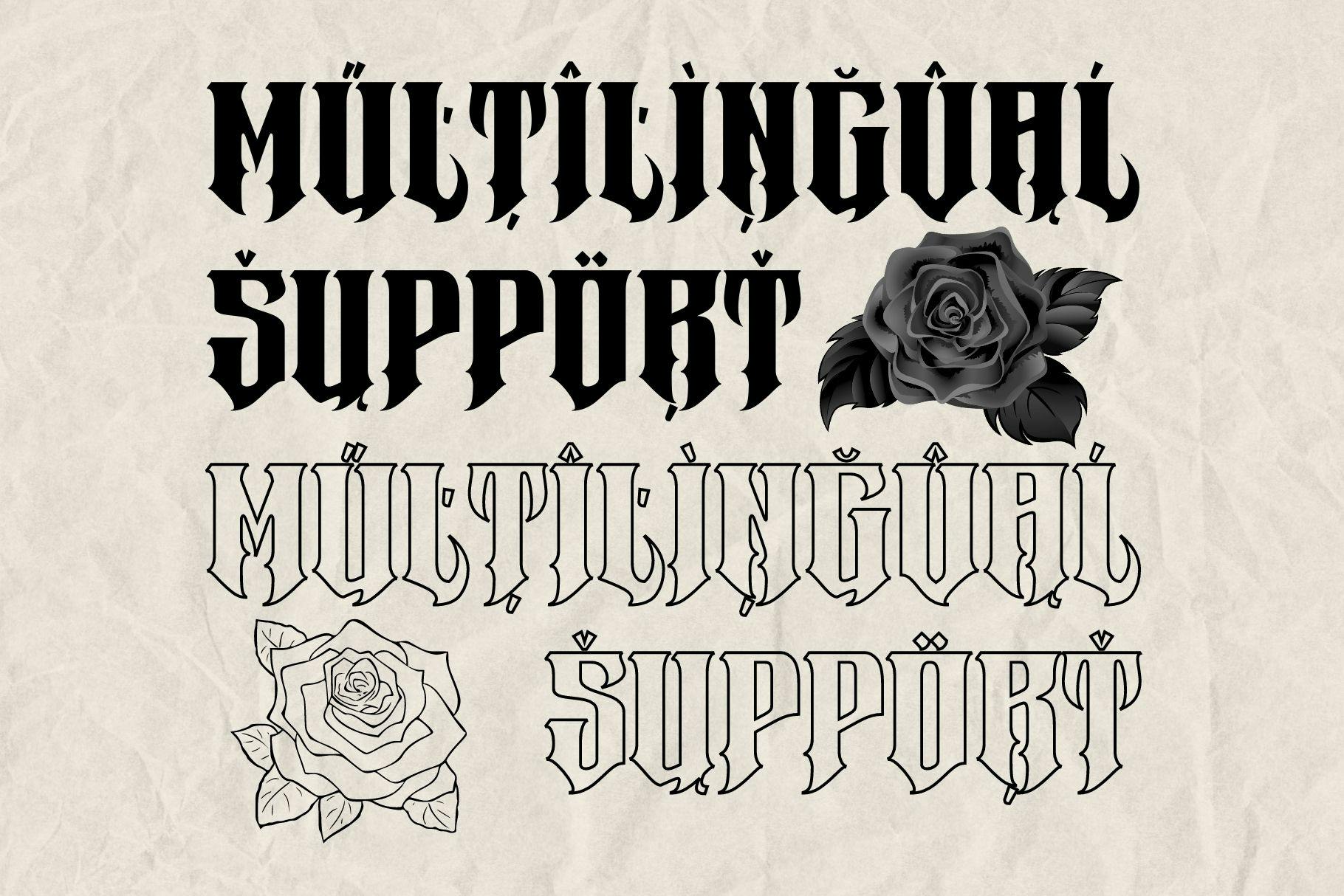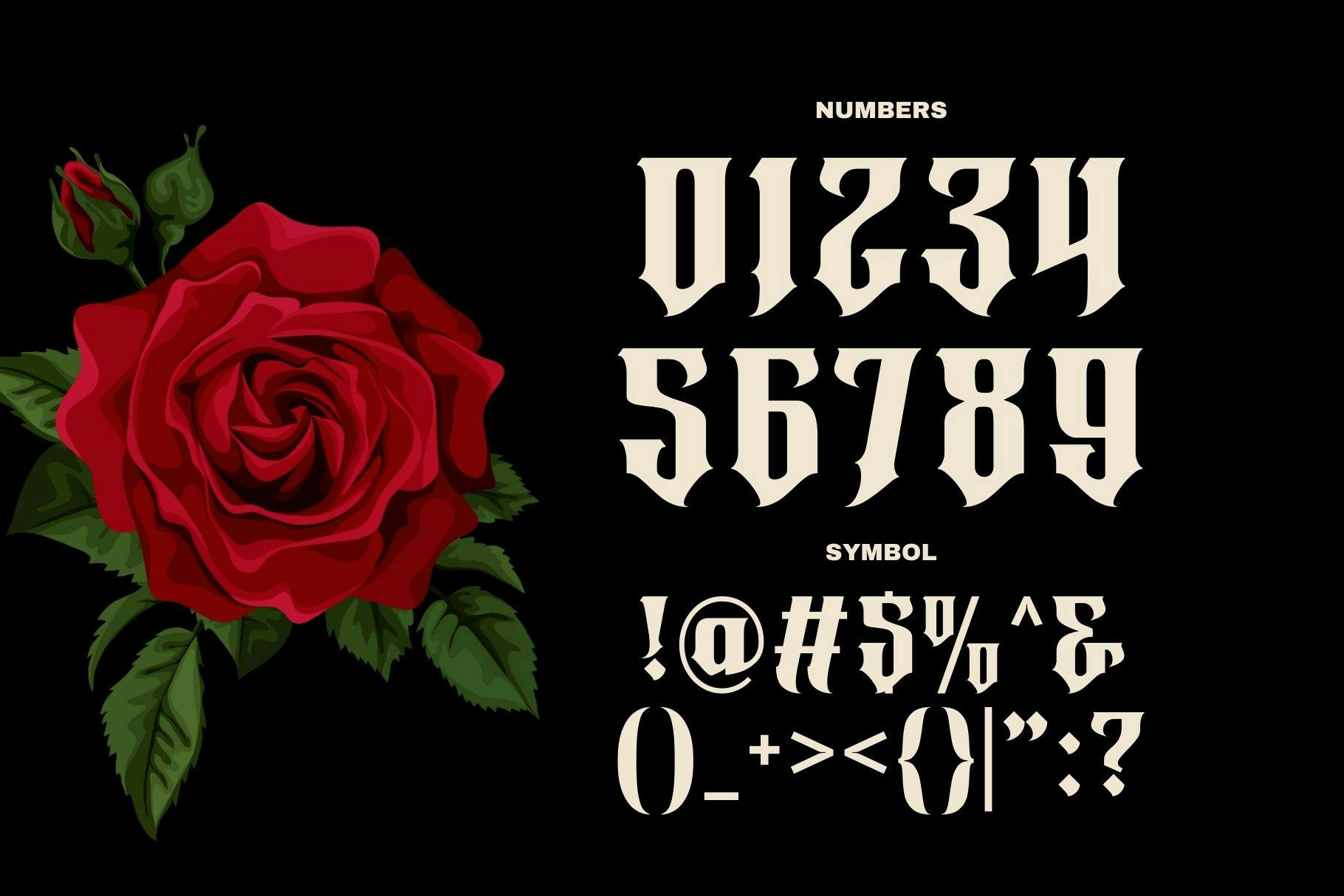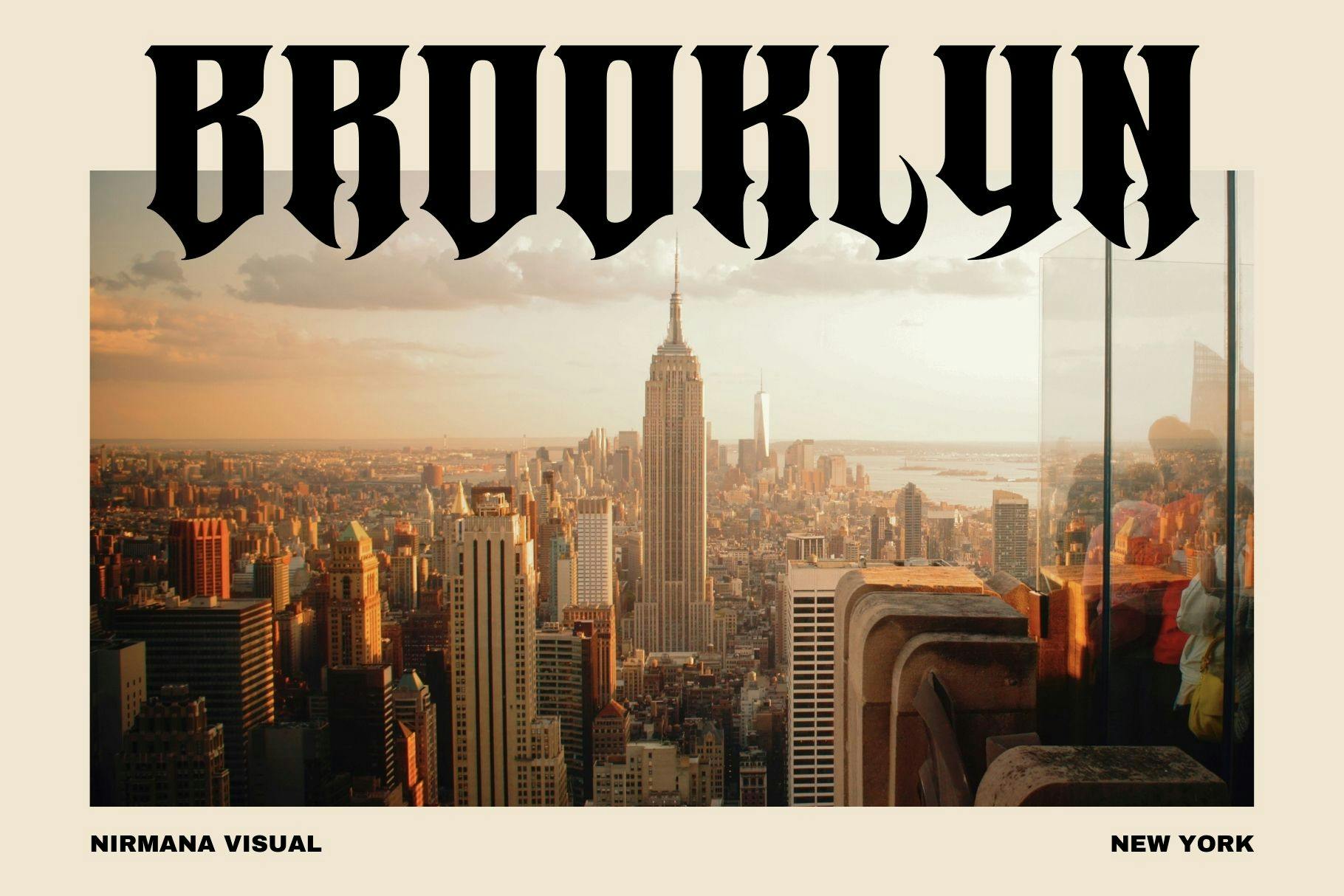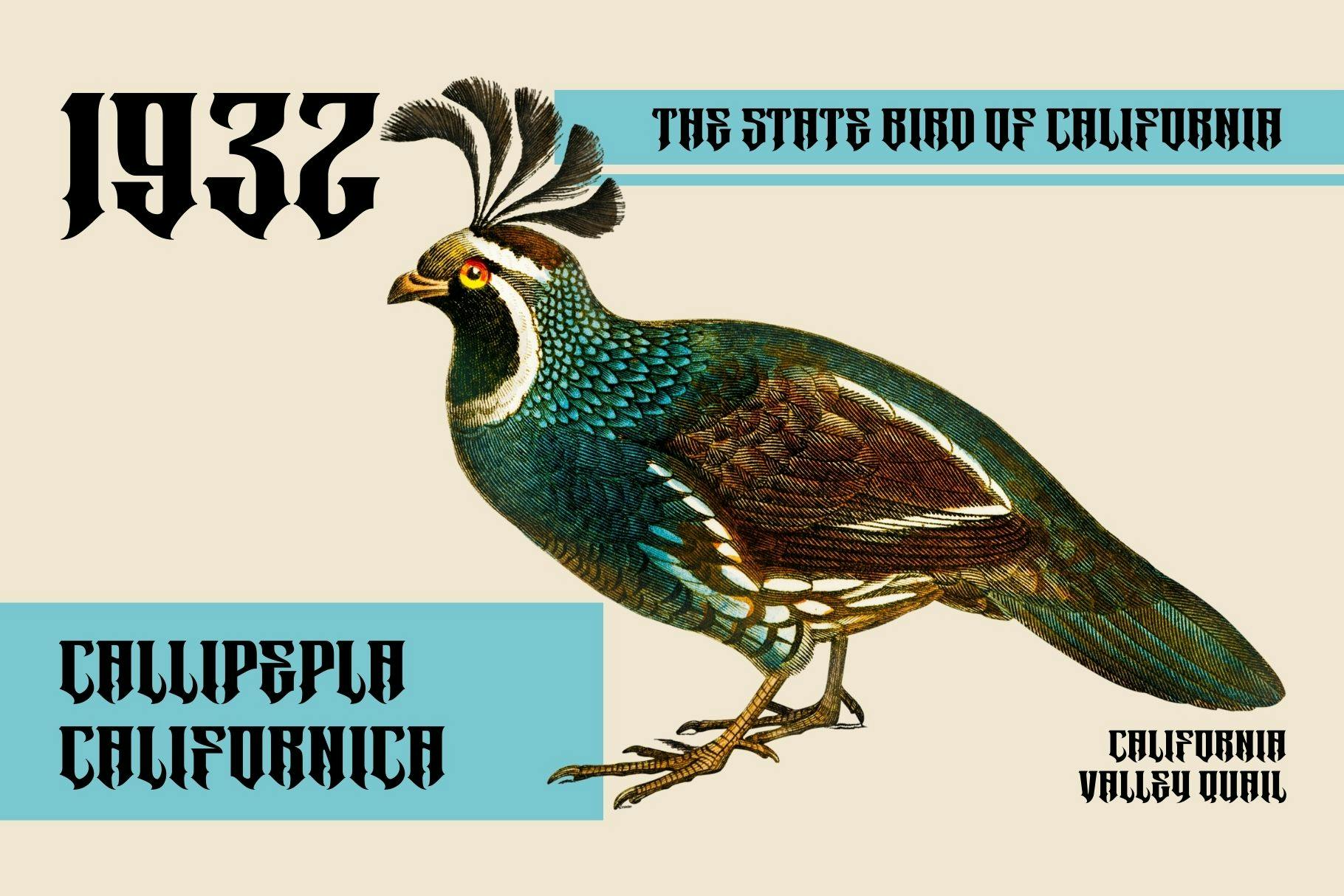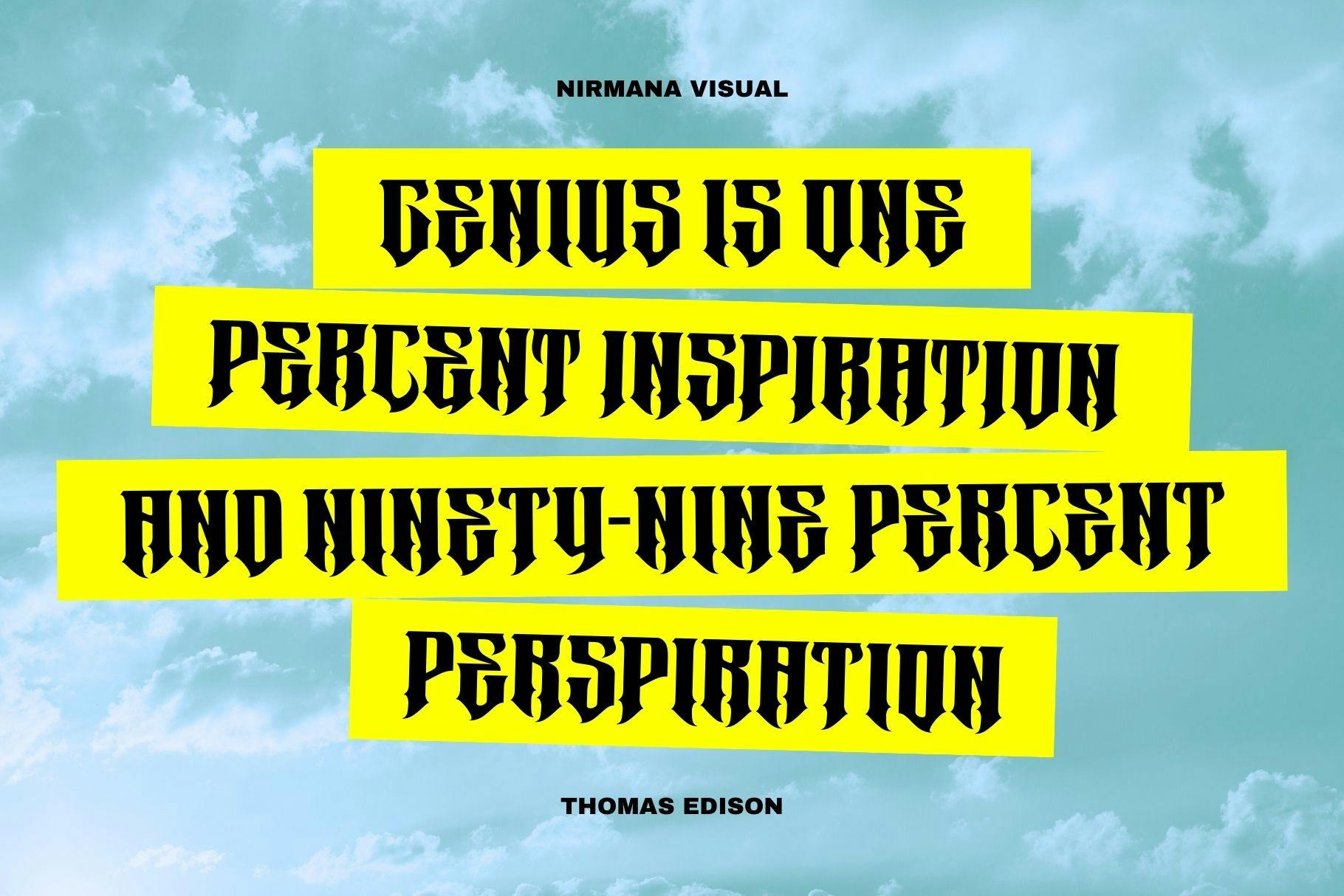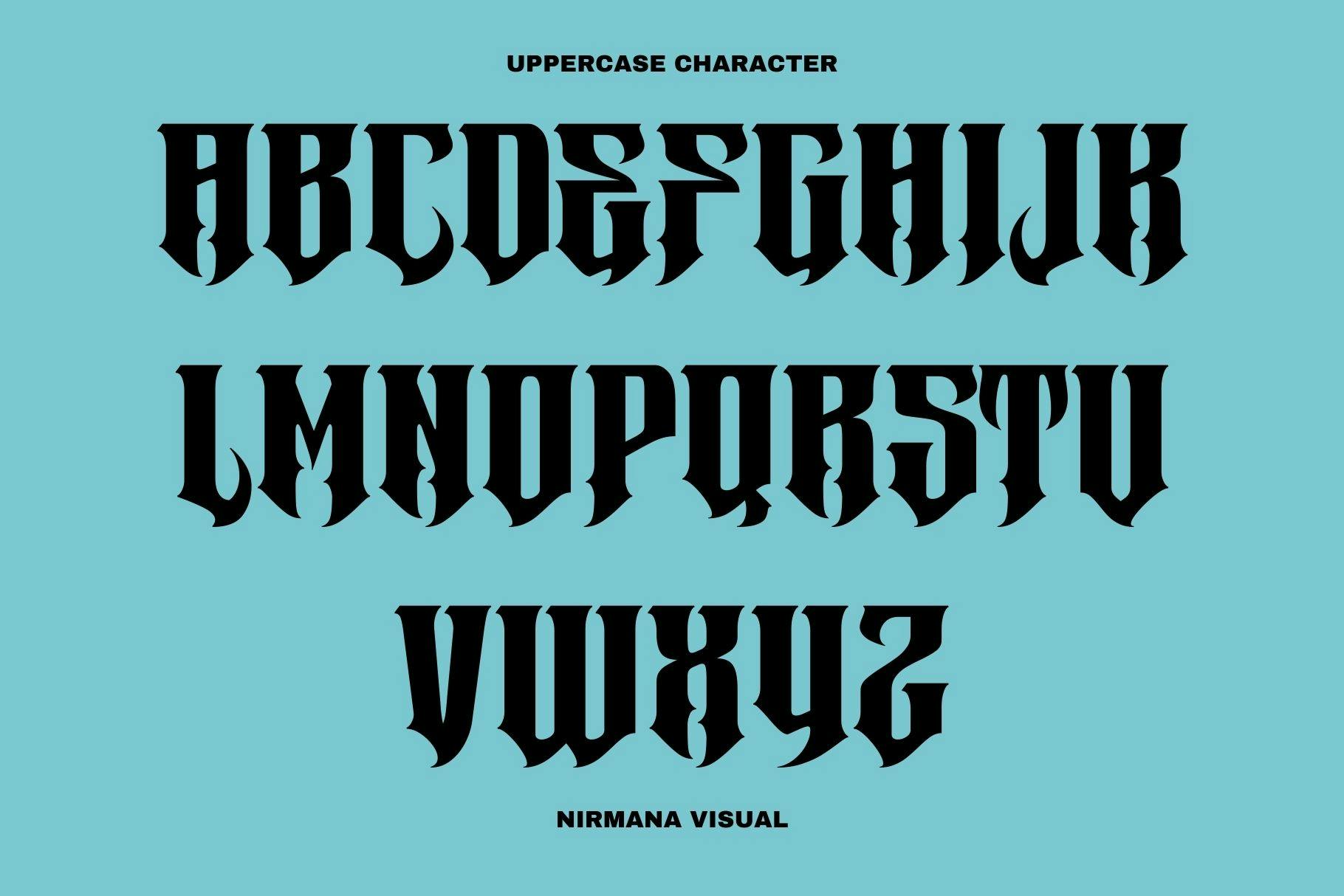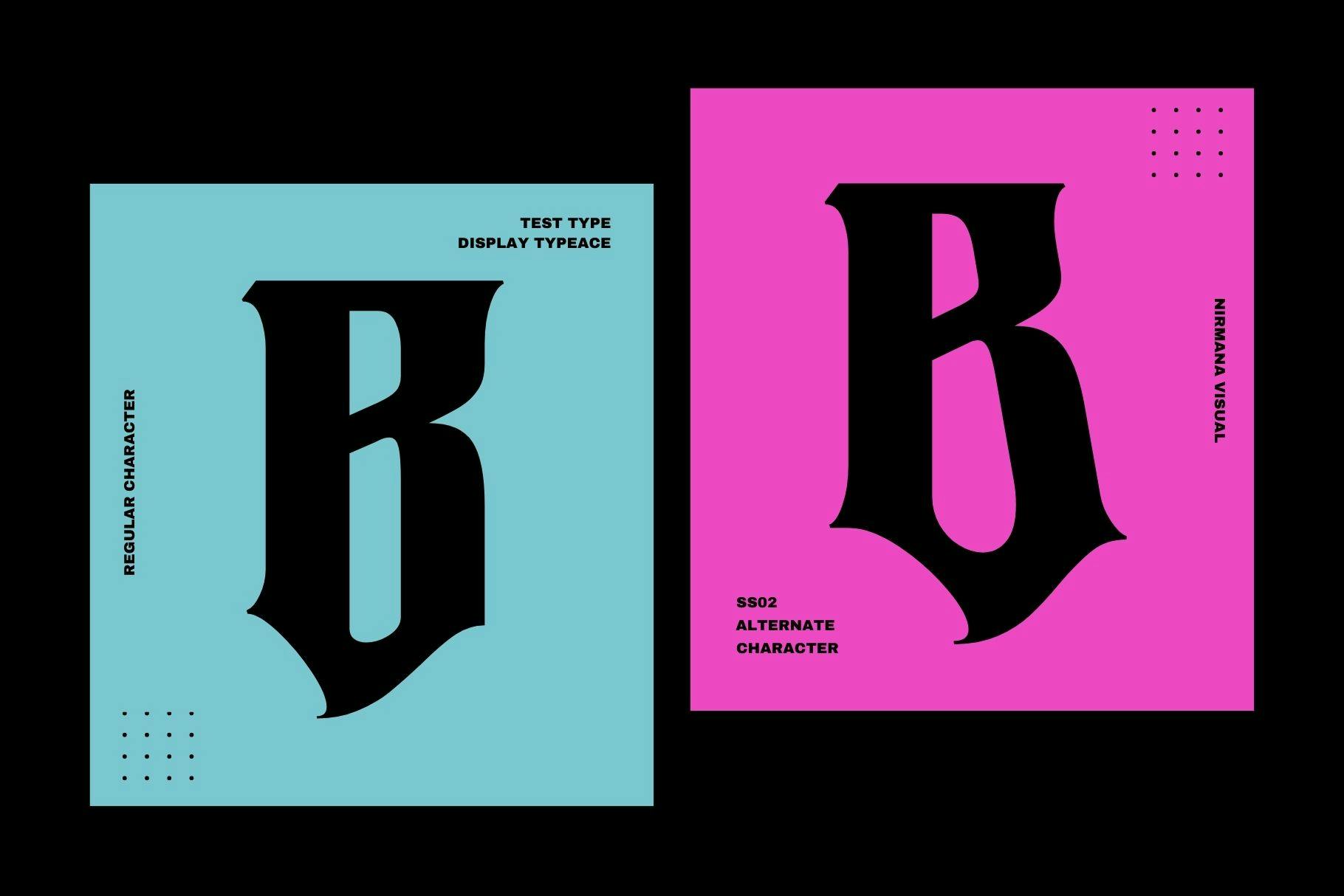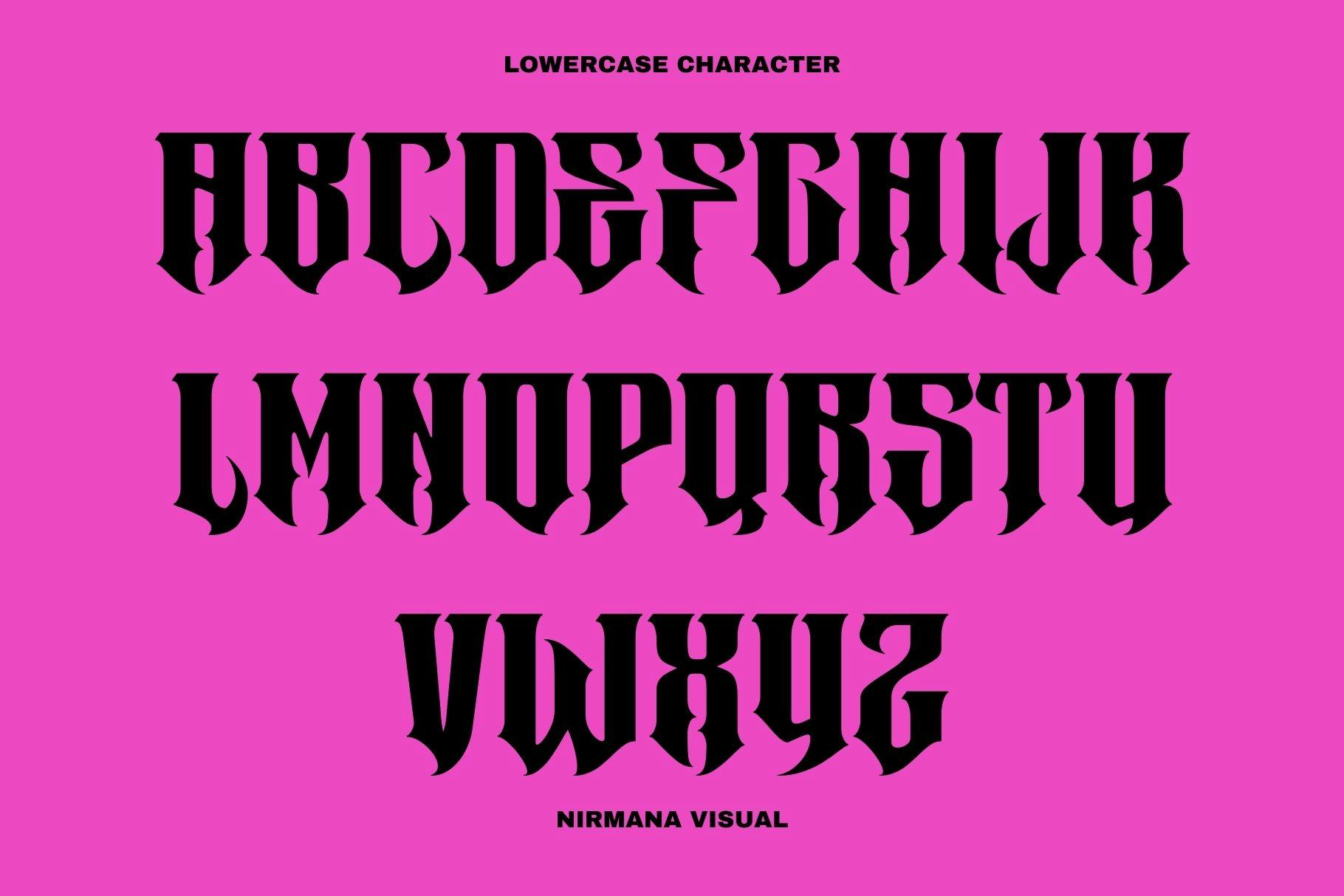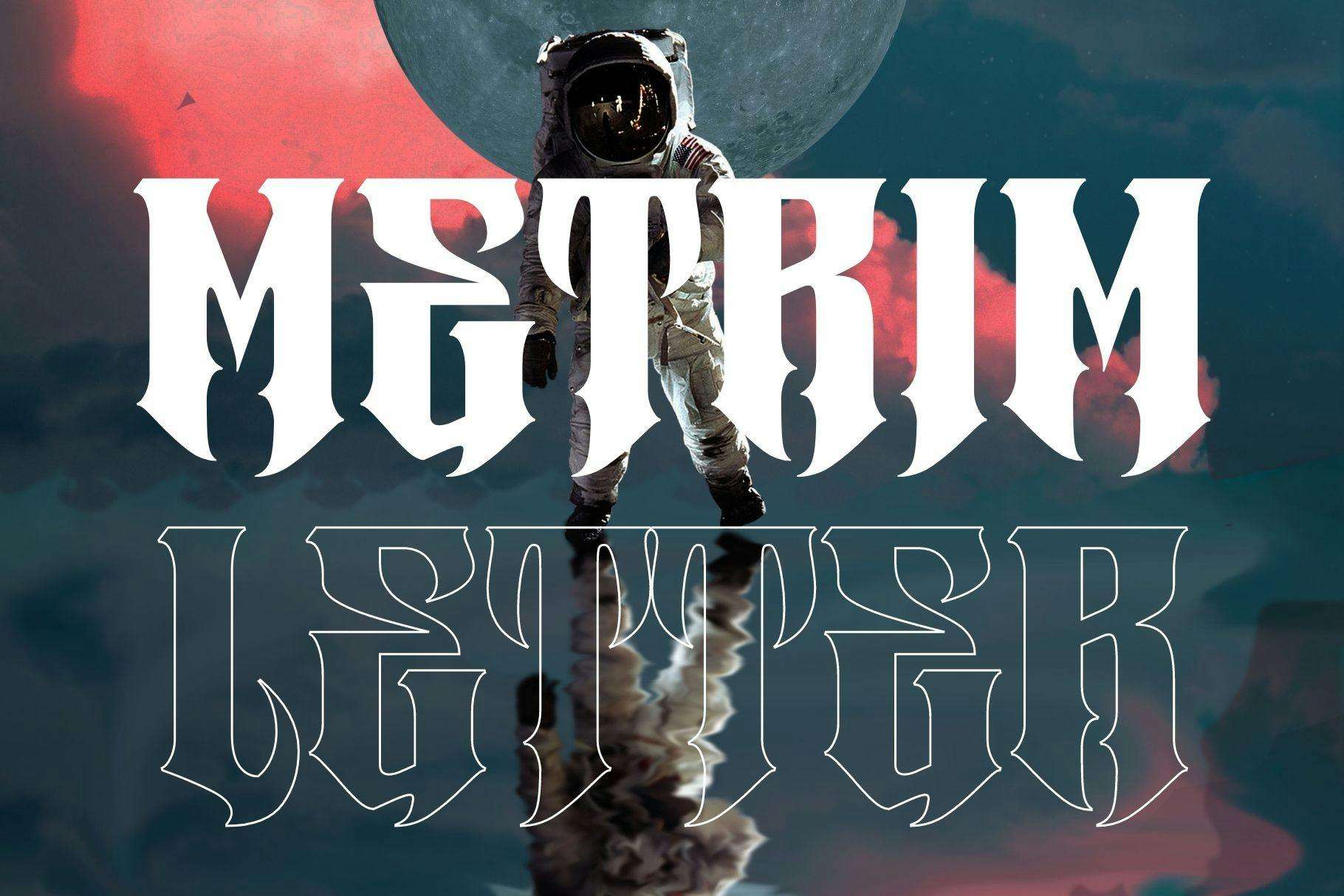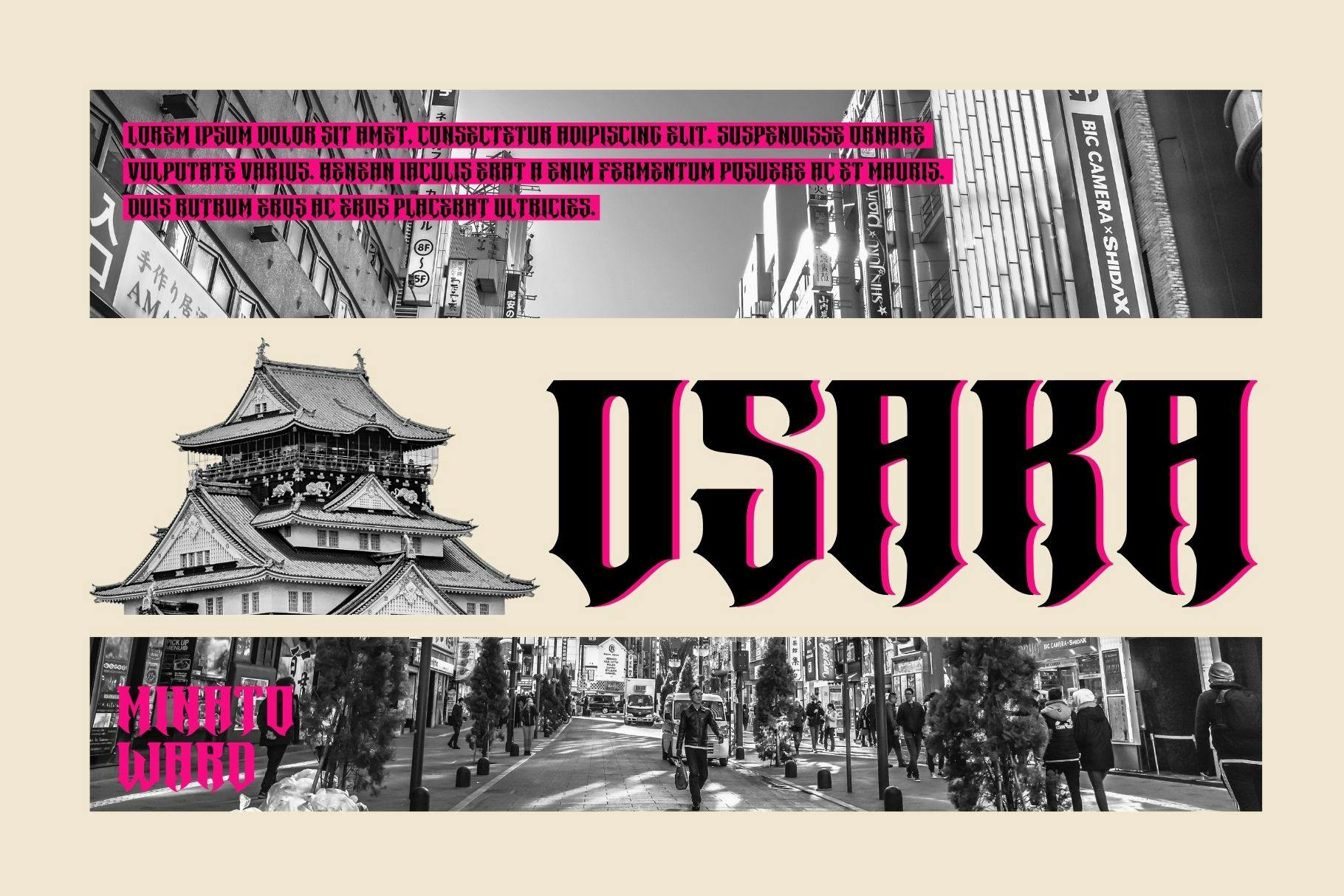
Metrim - فونت مدرن، نوع خط سریف نمایشی.
فونت متریم هارمونی زیبای تایپوگرافی را برای تنوعی از پروژههای طراحی، شامل لوگو و برندینگ، پستهای اجتماعی، تبلیغات و طراحی محصولات ارائه میدهد.